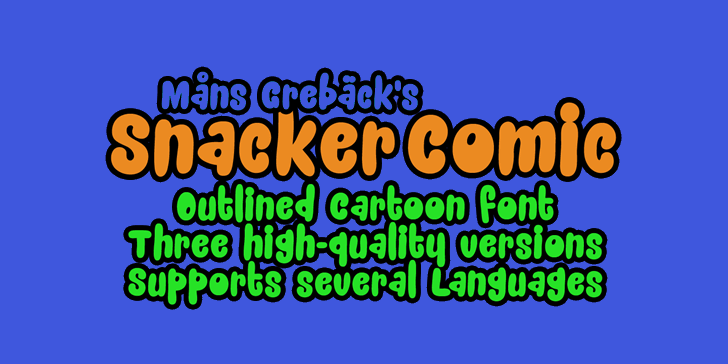
Snacker Comic font – Download Grátis
A fonte Snacker Comic é uma personalização única criada por Måns Grebäck no ano de 2013. Inspirada nos estilos desenhistas e cartunistas dos anos 90, essa fonte tem um charme encantador que combina o humor desconcertante com a simplicidade elegante, tornando-a perfeita para criações como rótulos de embalagens ou ilustrações. Ideal para designers e artesãos interessados em criar uma atmosfera descontraída e divertida em seus projetos, Snacker Comic é uma escolha versátil para qualquer designer que procura uma fonte comic personalizada. Com seu estilo reconhecível, a Snacker Comic pode fazer sua marca destaca-se em meio ao caos das redes sociais, mantendo uma aura de simplicidade e frescor, sem perder o poder do impacto. Agora disponível em um design mais moderno, ainda preservando os elementos que a tornaram tão popular, a Snacker Comic Personal Use Only é ideal para projetos que exigem uma fonte divertida com uma pegada vintage. A fonte foi criada pensando no design da interface de usuário, embalagens de produtos e aplicativos móveis. Ideal tanto para o uso pessoal quanto para projetos comerciais onde se deseja adicionar um toque de humor a qualquer layout ou arte digital, Snacker Comic é uma escolha ótima para qualquer designer em busca de uma fonte que não deixará ninguém indiferente.